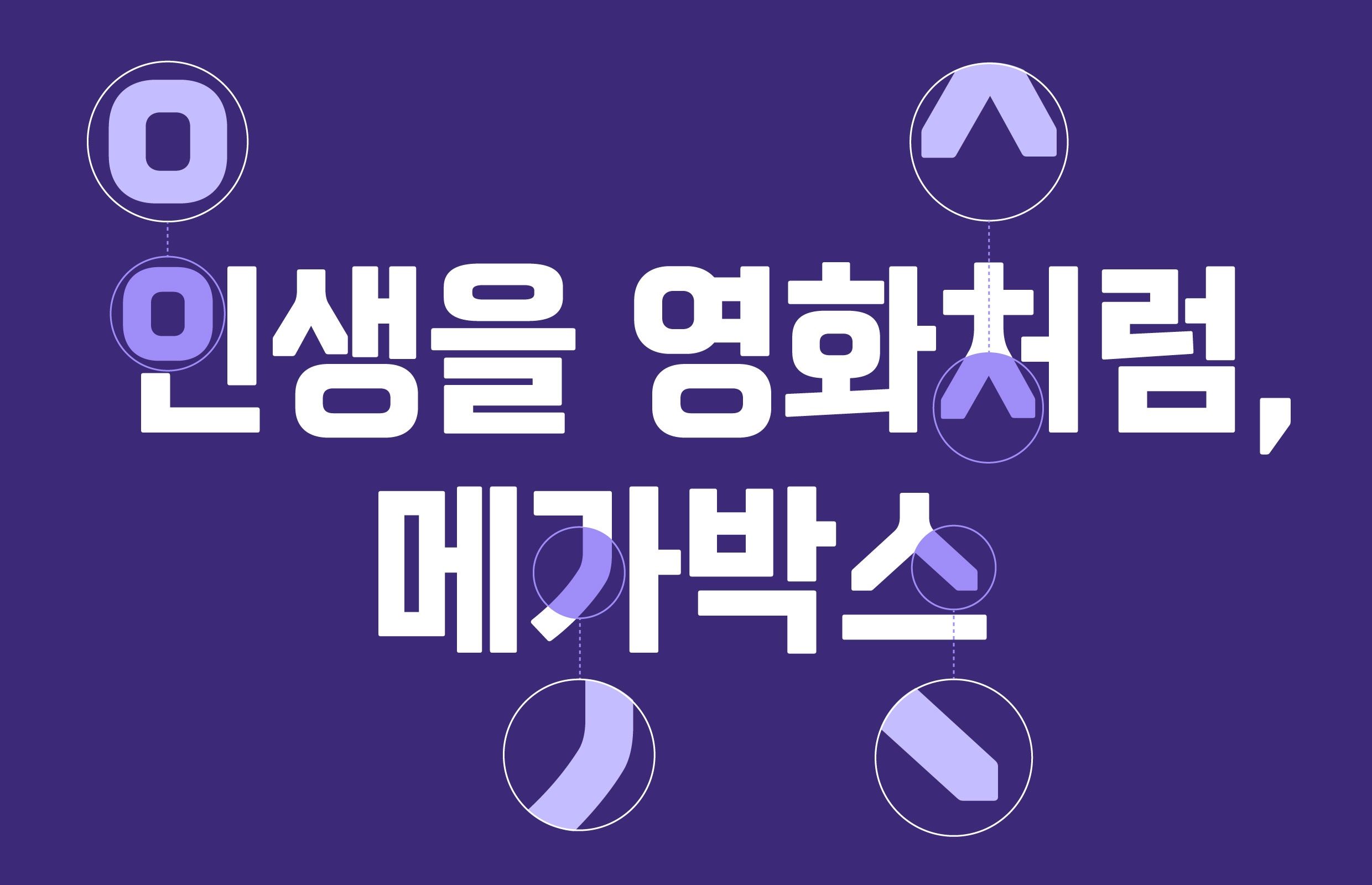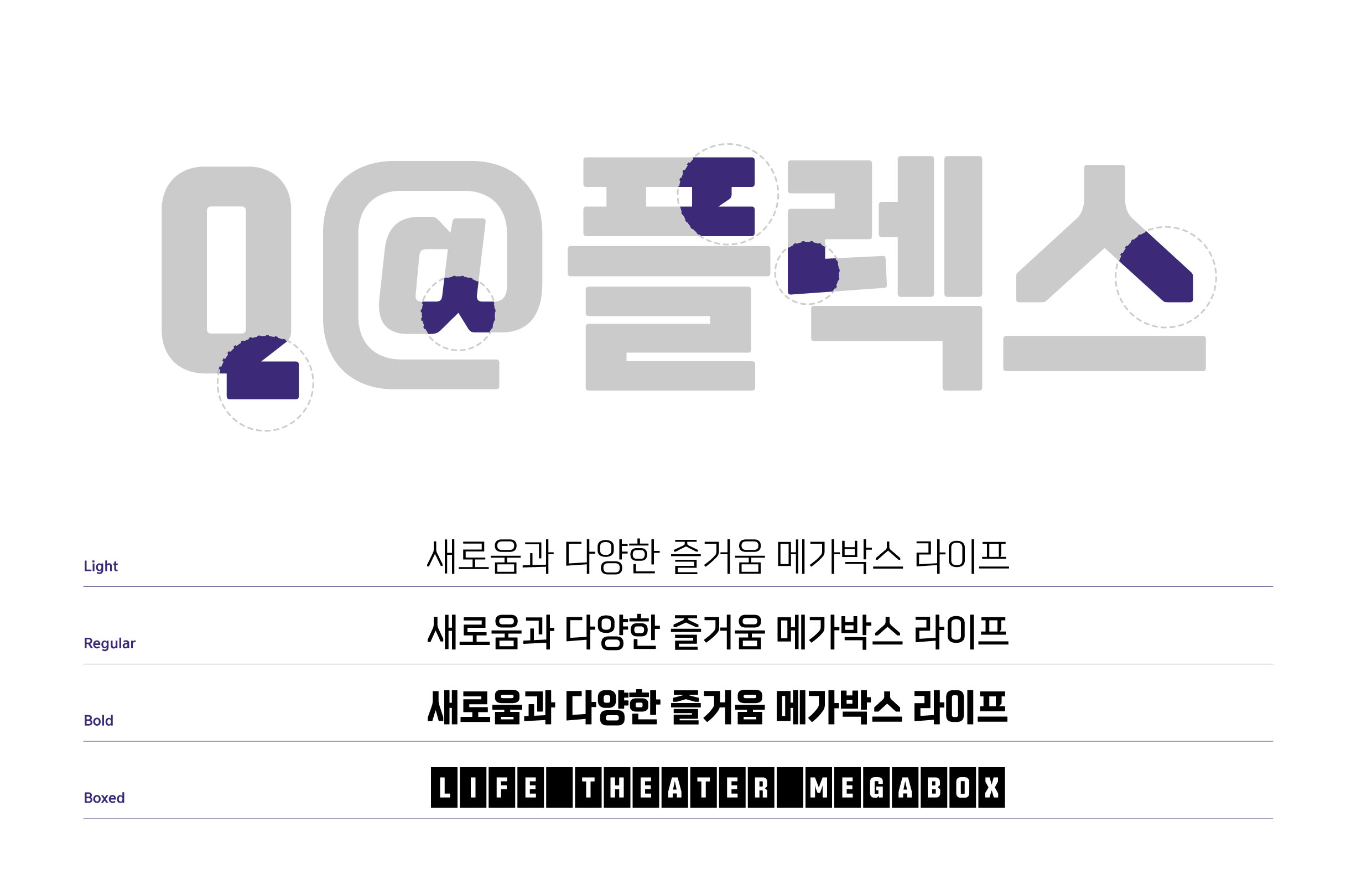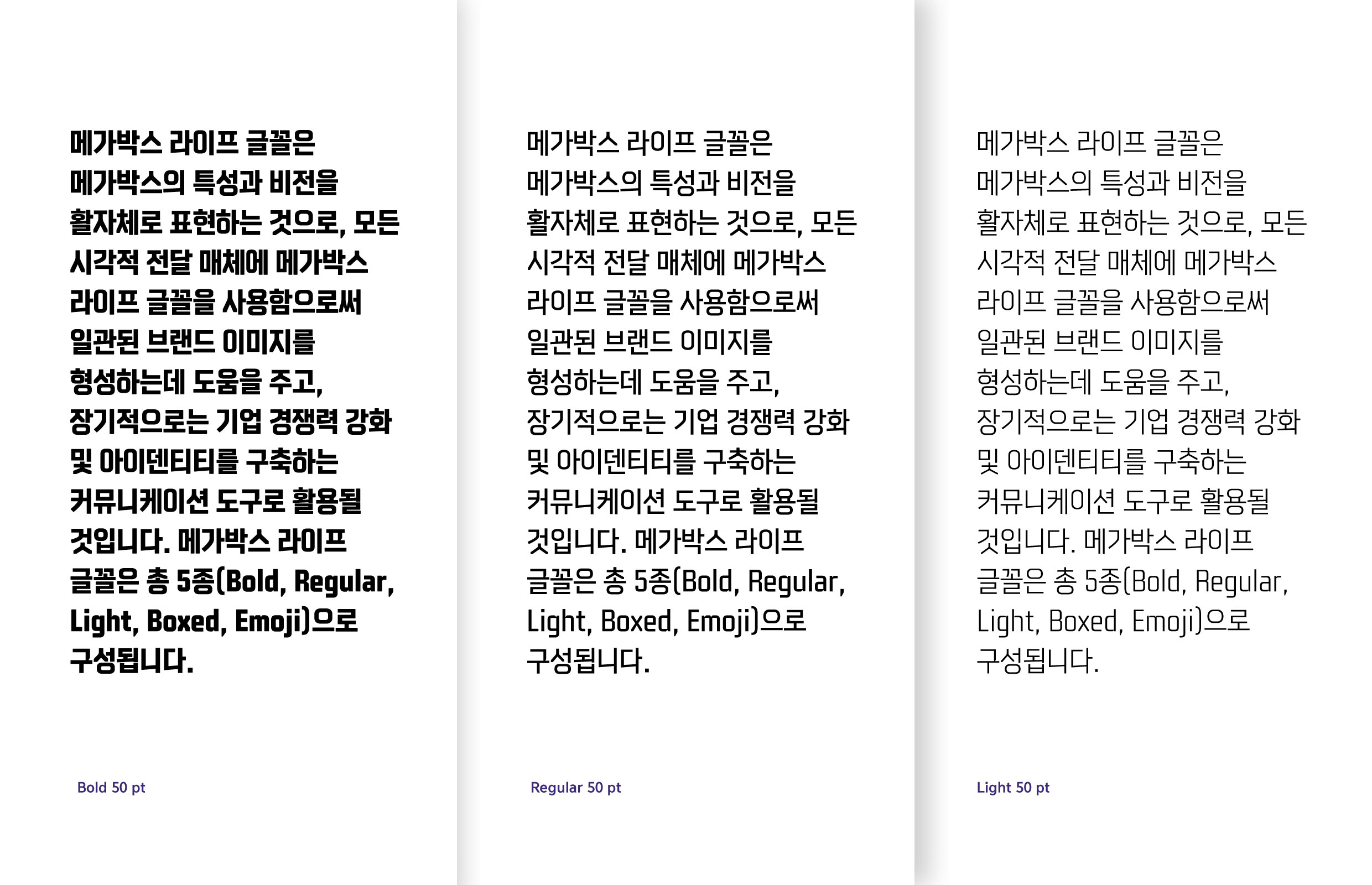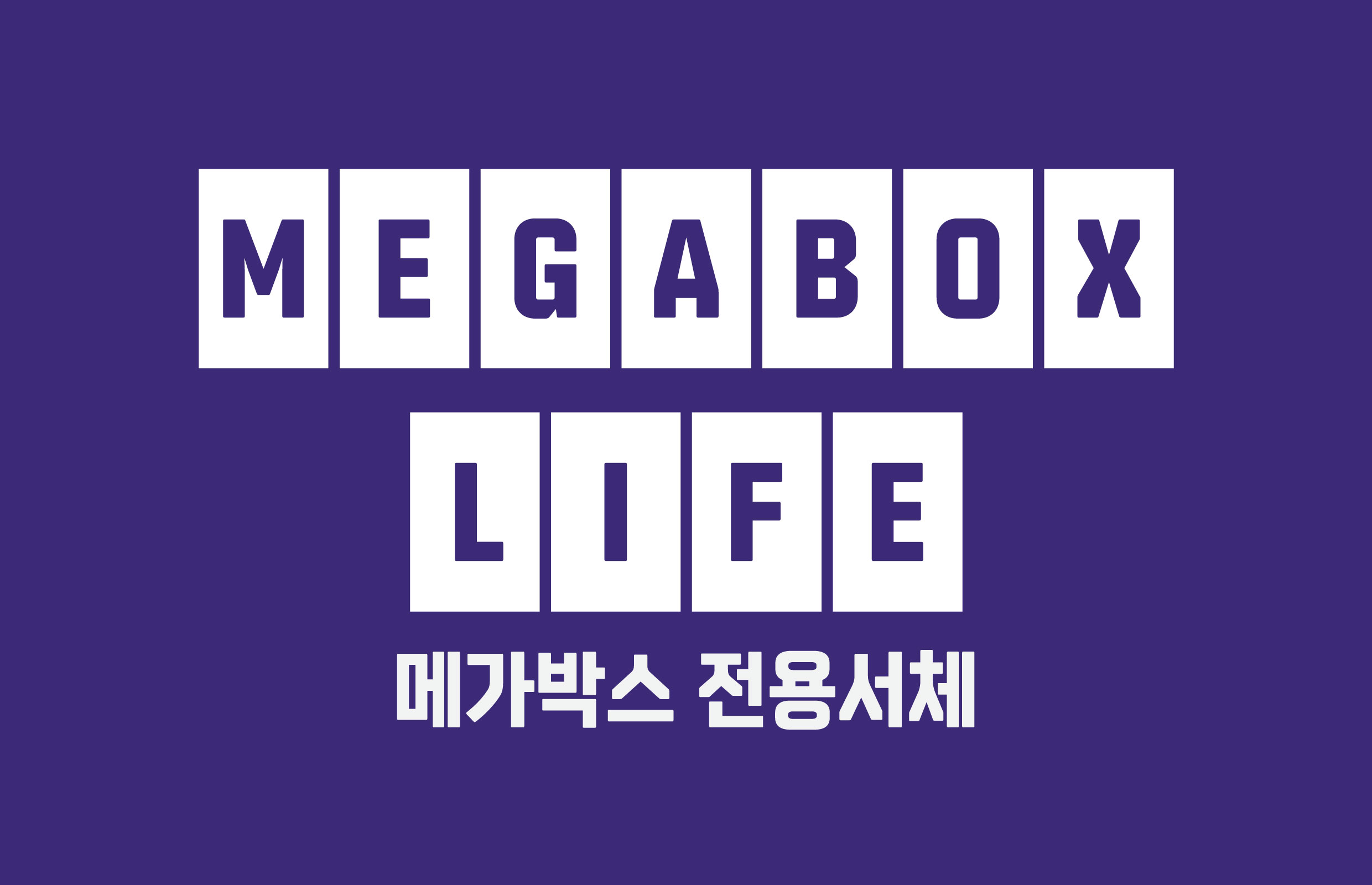
메가박스
메가박스 [메가박스 라이프]
온오프라인 미디어와 물리적 공간 어디서나 사용하기 적합한 인더스트리얼 서체. ‘황금 비율의 박스를 조각해 간다’라는 의미를 담아 디자인하였다. 한글, 라틴 알파벳과 함께 박스 타입 서체와 픽토그램까지 함께 개발하여 일관된 브랜드 이미지를 형성하고, 사용성에 디테일을 더한 점이 특징이다.